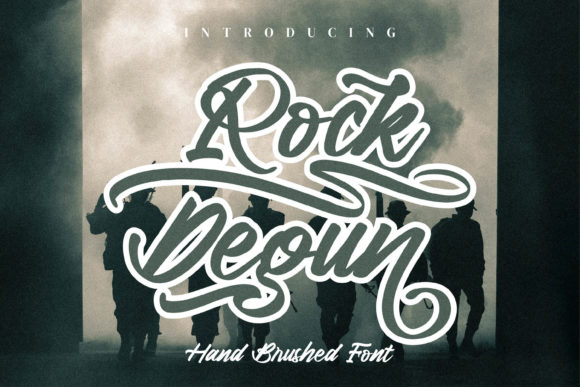
[Creativefabrica] Rock Degun Font
Rock Degun - это классный, скорописный и модный рукописный шрифт.
Добавьте его в каждое свое творение, требующее веселого, стильного штриха, и вы будете в восторге от конечного результата.